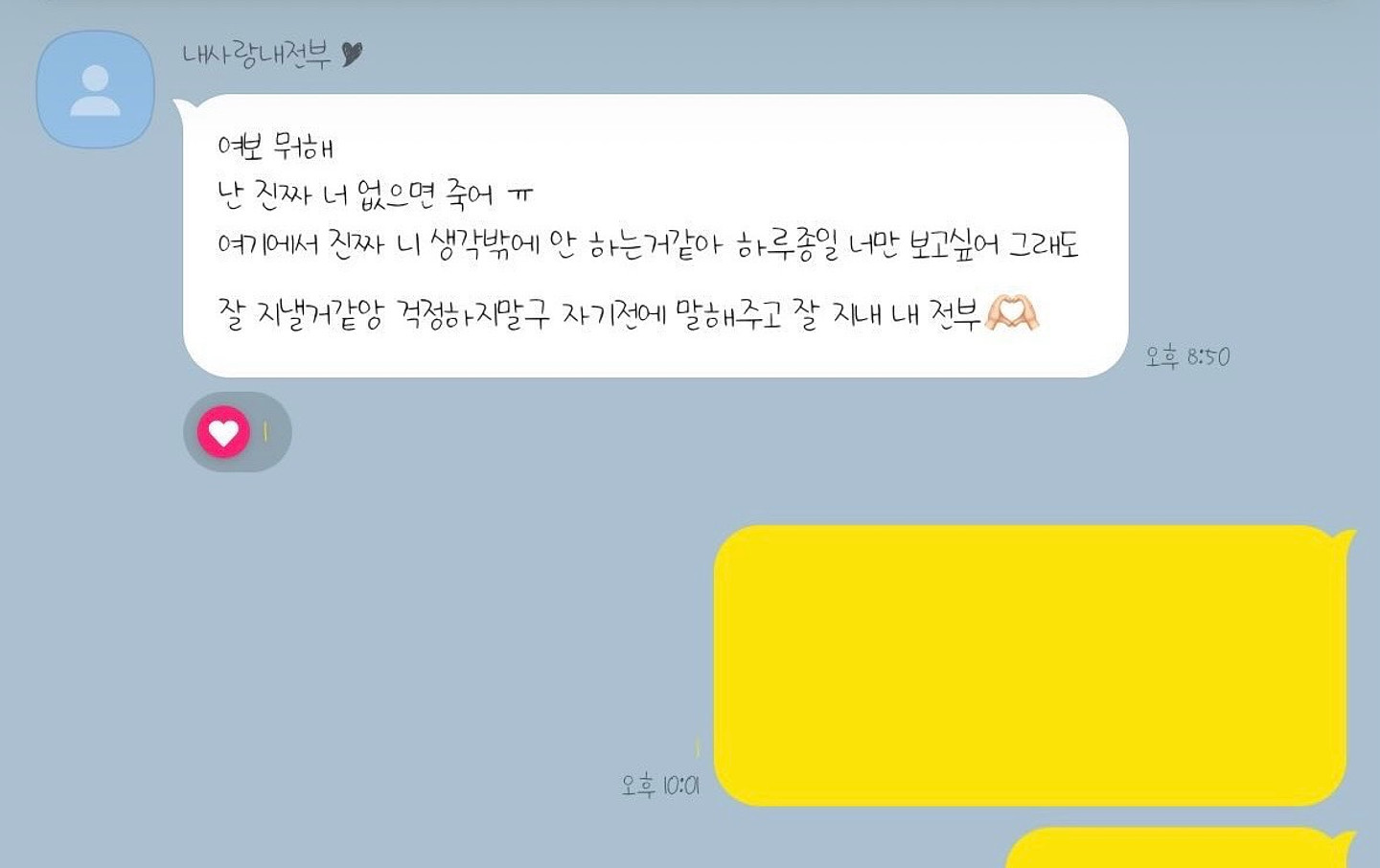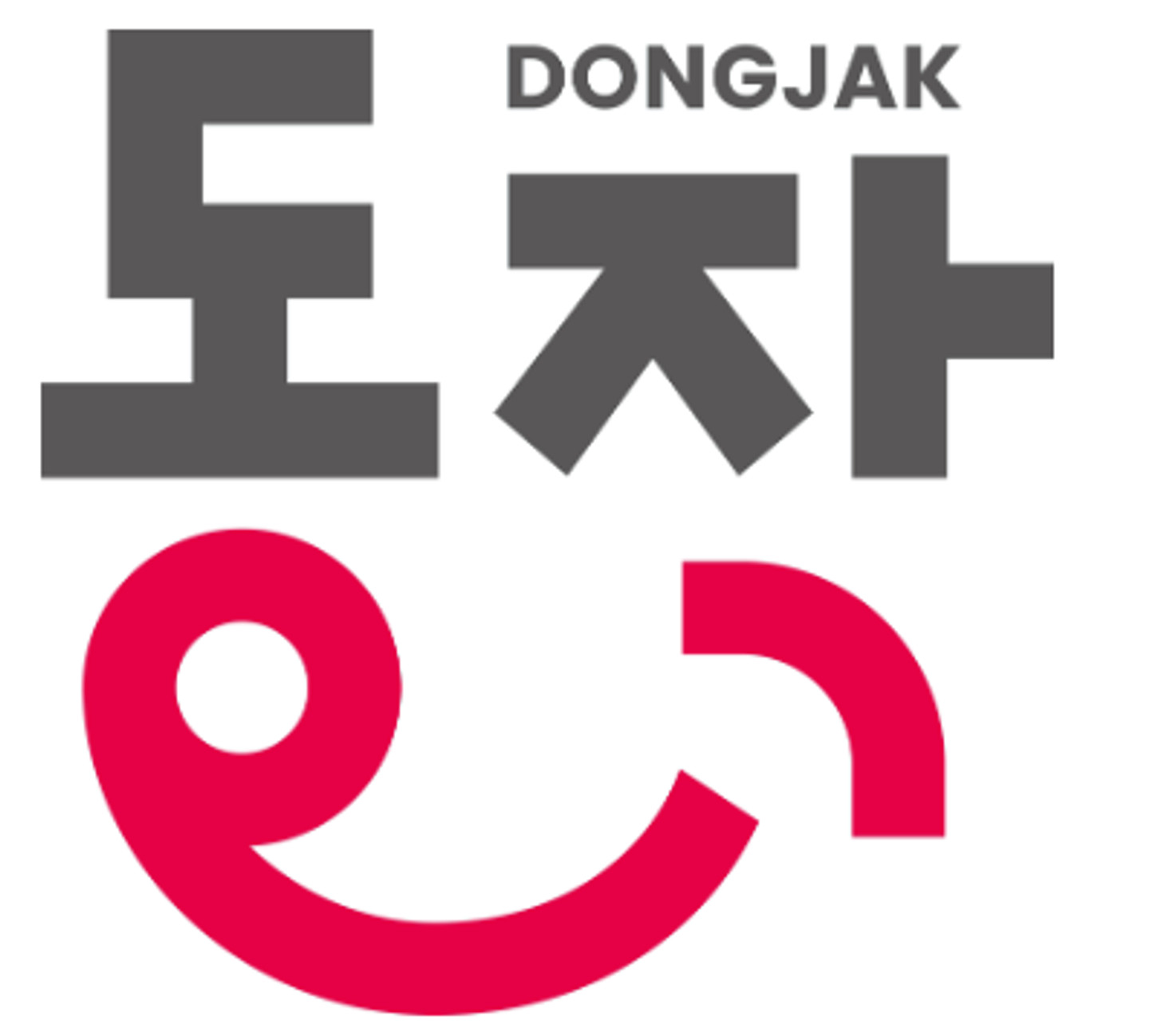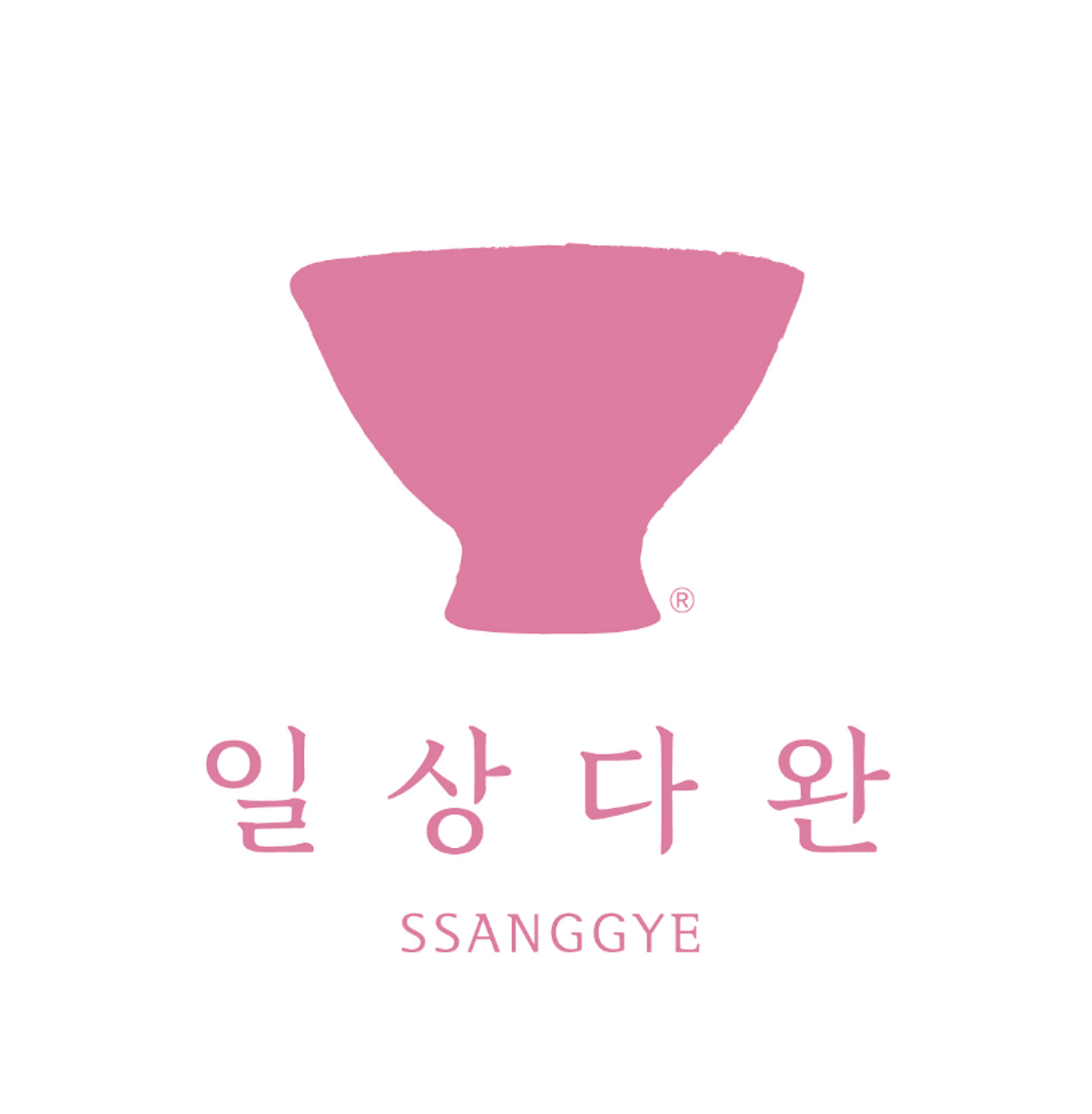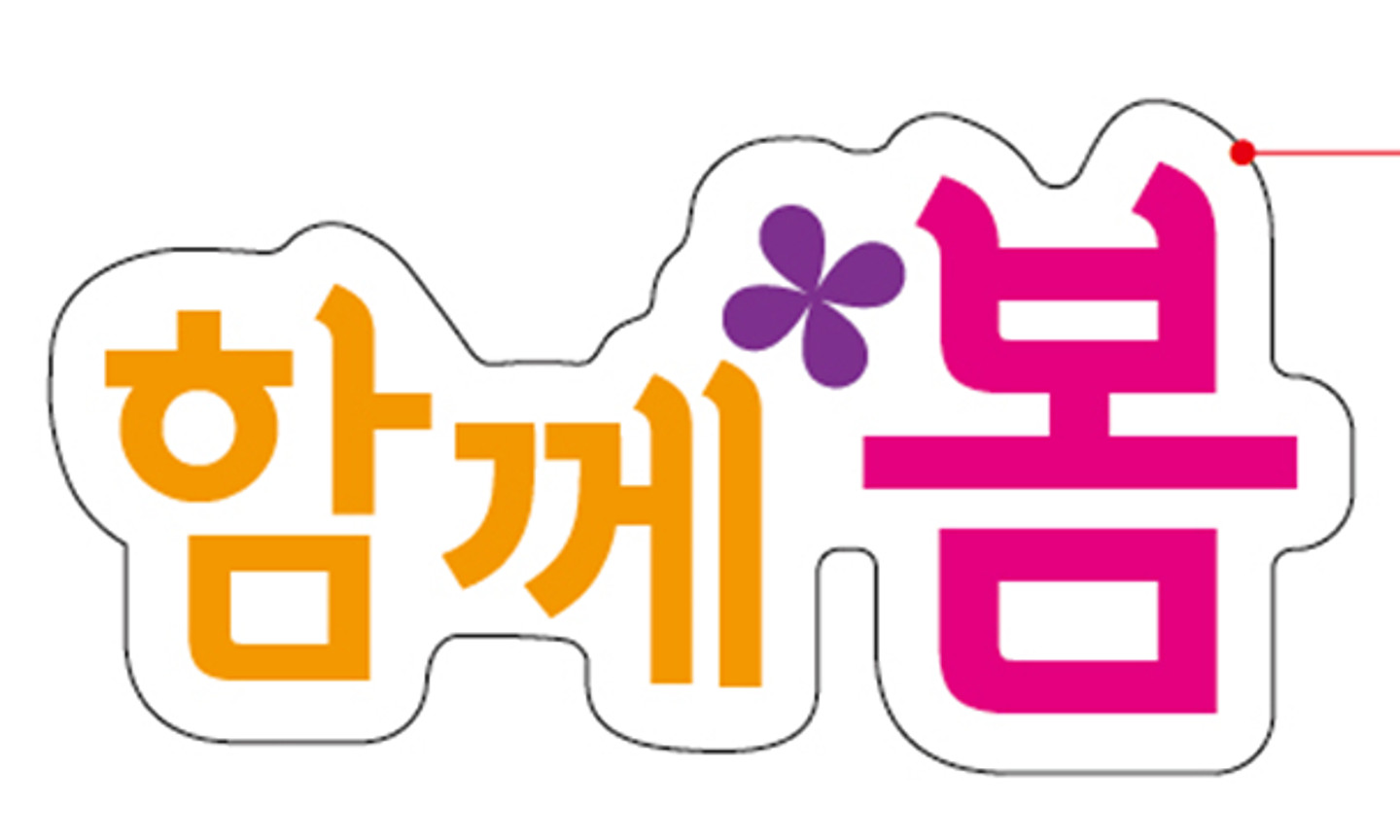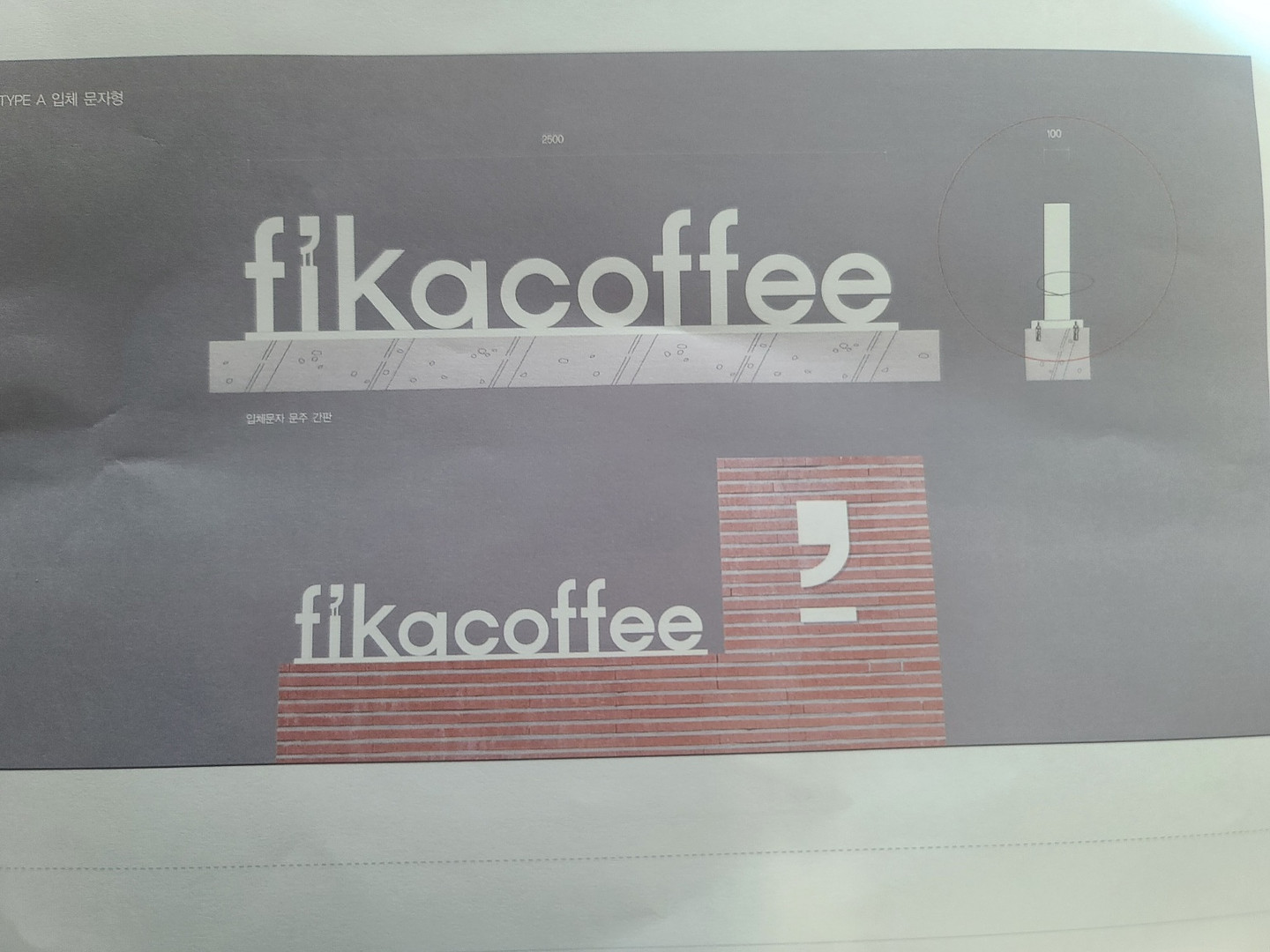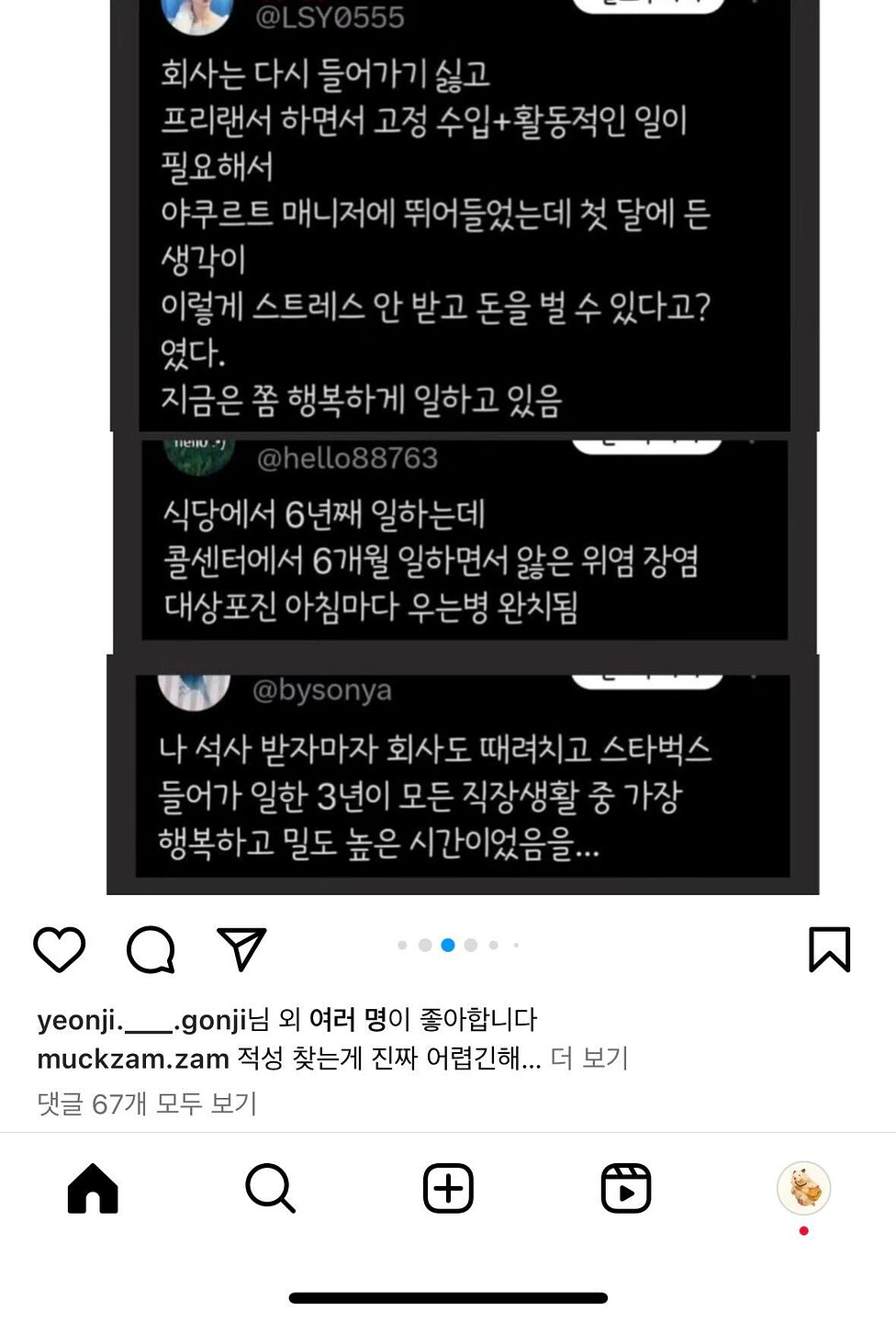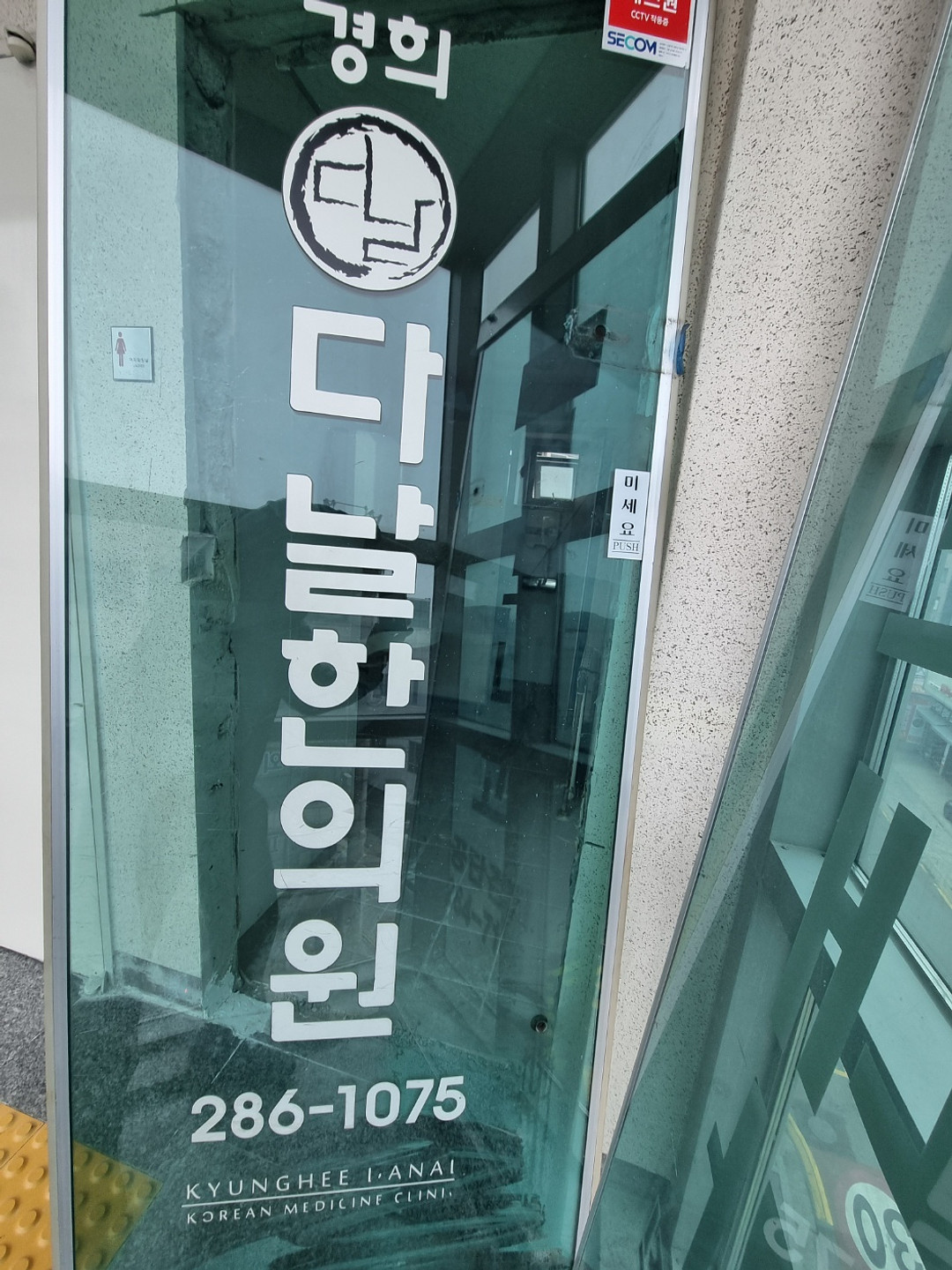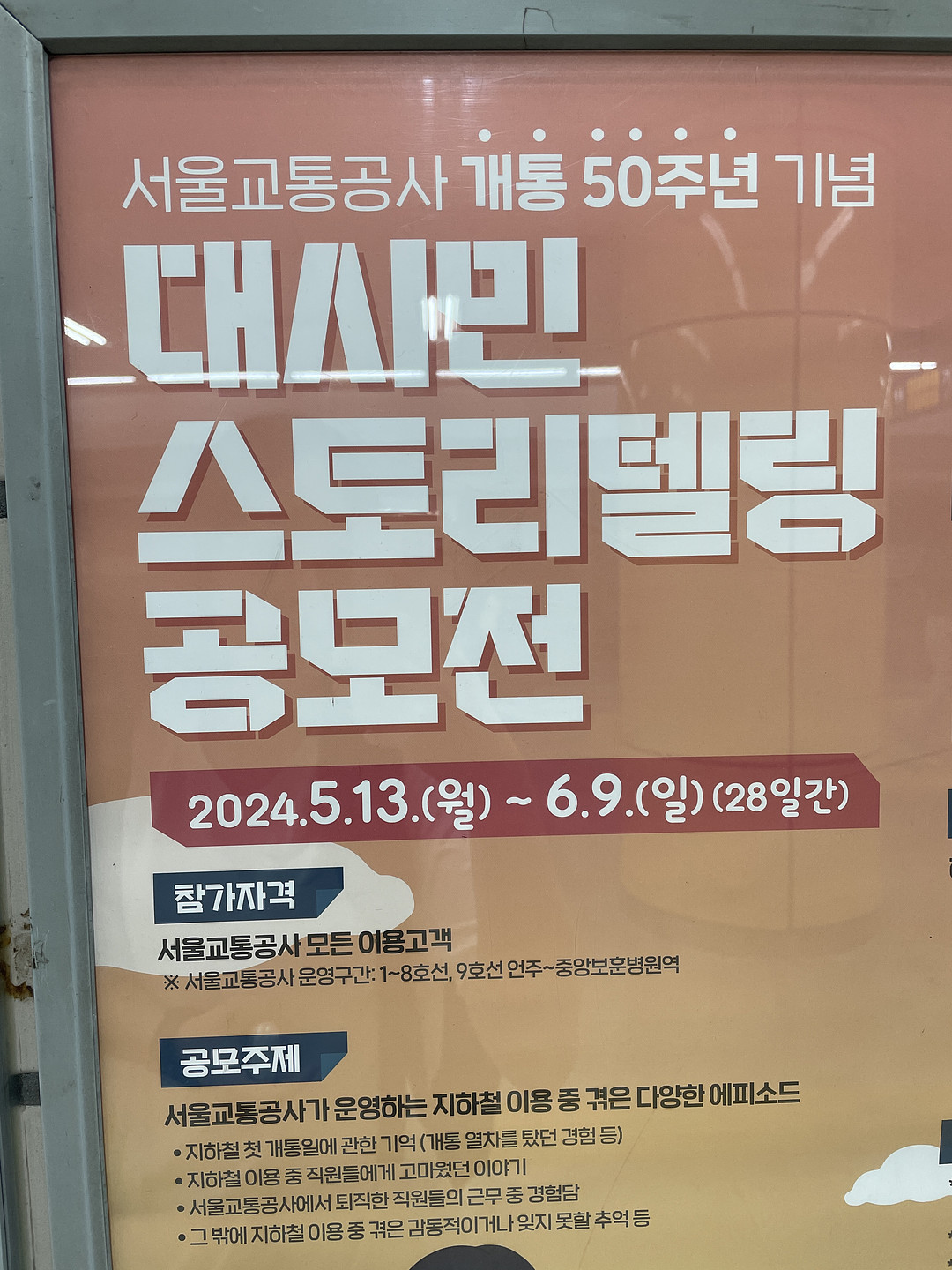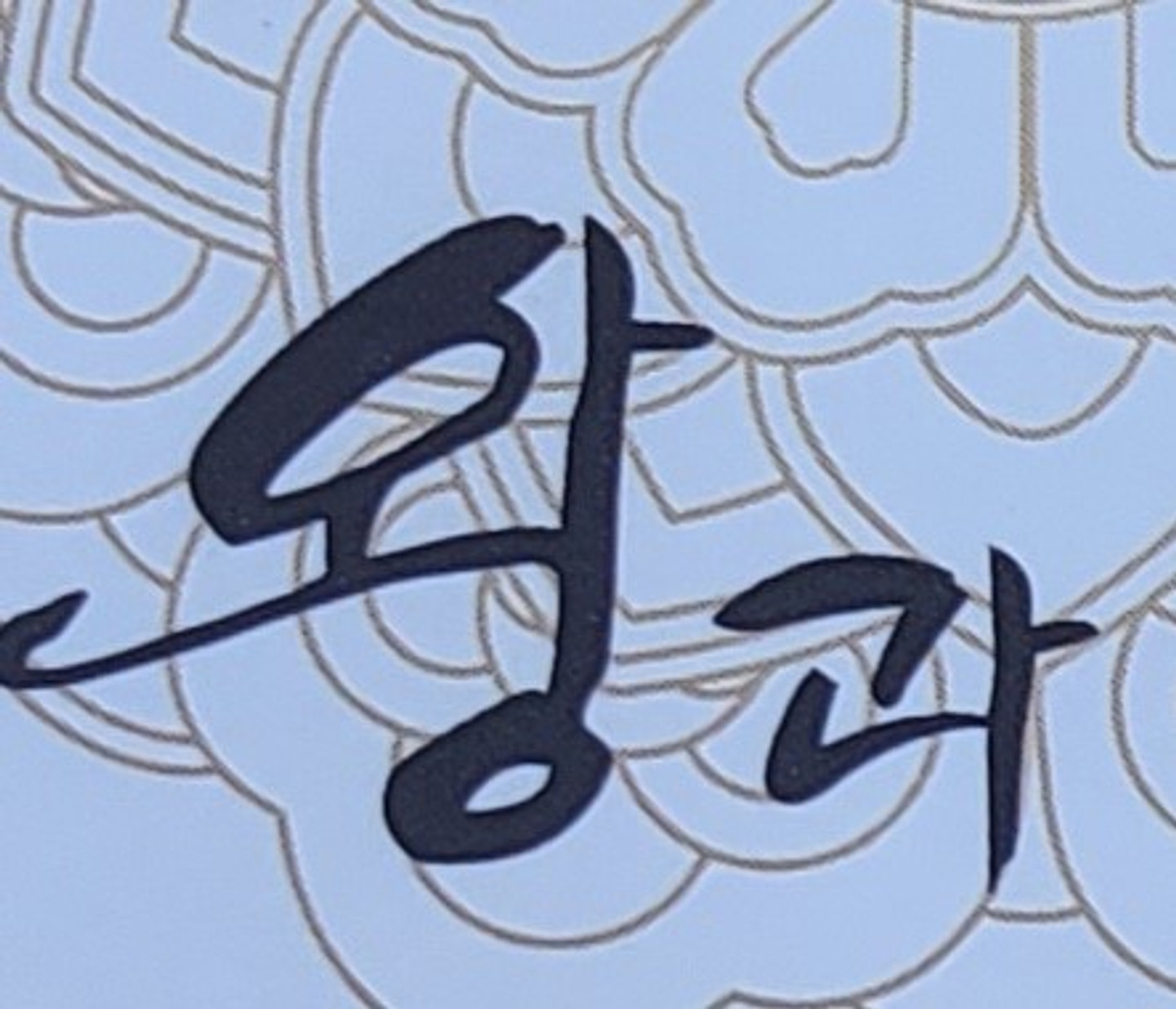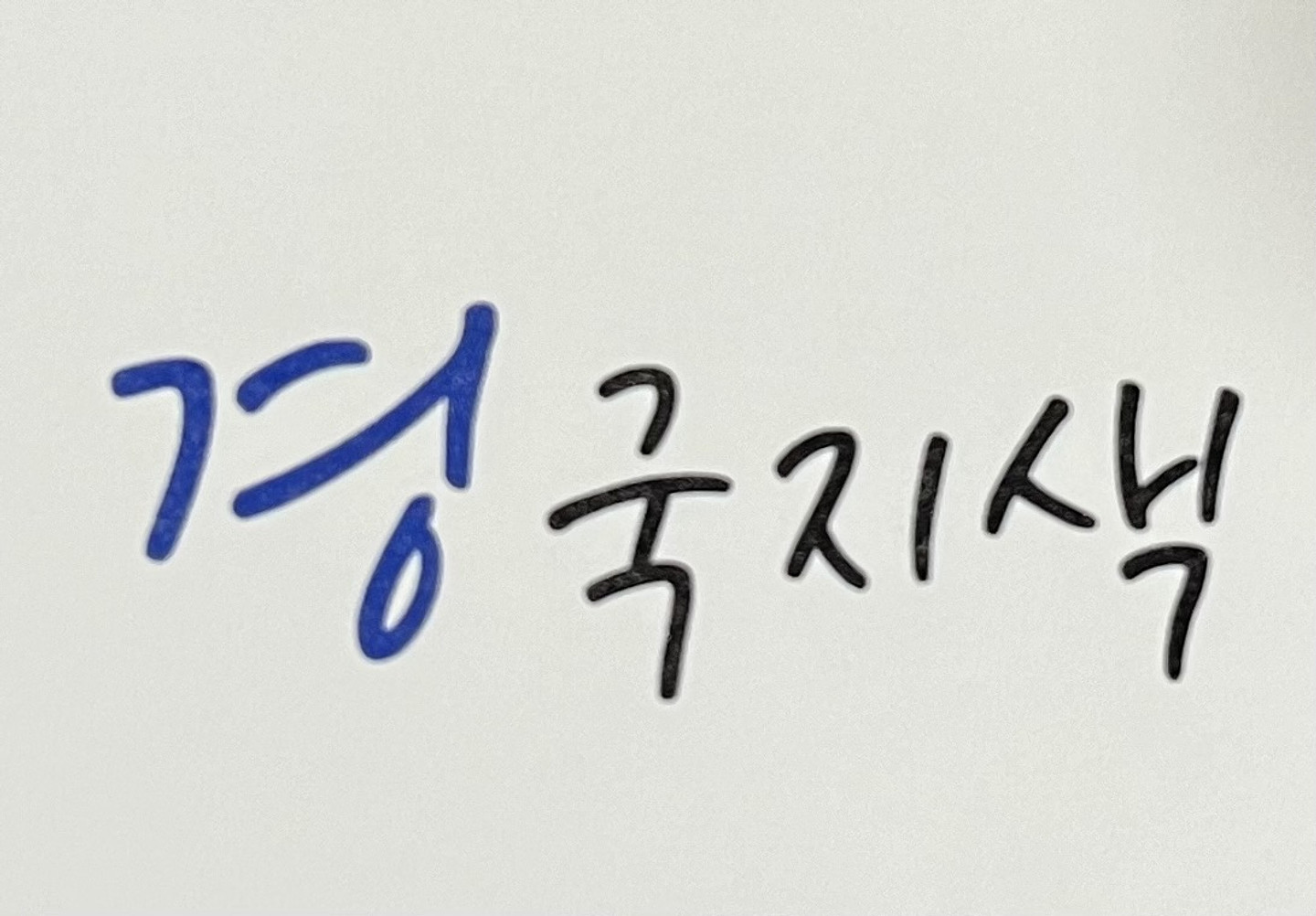
아모레퍼시픽 홈페이지에 있는 폰트인데요! 아모레퍼시픽의 폰트 아리따는 아닌데 홈페이지에 요런 폰트도 있어서 궁금해서 문의드립니다!
궁금해요 ㅠ
ㅇ부분이 태나다체인줄 알았는데 태나다체와는 다르더라구요 혹시 어떤 폰트인지 아실까요 ?
타이틀과 본문에 각각 어떤 폰트가 사용된 걸까요?
검색햇는데 ㅁ 비슷한건 많은데 딱떨어지는 폰트를 못찾았습니다..
요거 영문 폰트 뭔지 아시는 분?
KARMA BLACK CUBE 폰트가 궁금해요… 비슷한거라도 알려주세요 감사합니다
이 폰트 아시는 분 계실까용??
이거 배경있는 폰트로 쓸건데 폰트가 뭔가요?
제목폰트랑 문학과지성사 폰트 뭘까요~?
이 글씨 알려주시면 감사하겠습니다!!
폰트 알고 싶어요
여기 사용된 폰트 궁금합니다.
유혜주 유튜브 폰트입니다!
저 DAY3 폰트 뭘까요
우연히 발견했는데 어떤 폰트인지 궁금해요!
유혜주 브이로그에 나온 폰트입니다
폰트 알려주새용 ㅜㅜ
익스큐즈미...폰트.....알려주세y0... 감삼다 ㅠㅠ
폰트명
비누비누 브랜드에서 쓰는 이 한글폰트좀 알려주세요ㅜㅜ
이거 영문 폰트 뭐죠? 예전에 찾았던 것 같은데 못 찾겠네요 ㅠㅠ
안성재가 여는 미식의 공간 | LG 디오스 오브제컬렉션 김치톡톡 광고에서 쓰이는 이 폰트는 어떤 폰트인가요? 유료라면 비슷한 무료폰트 알려주세요.
무슨 폰트인지 너무 궁금합니다아아앍....,.....,,,,,,,!!!!!!!
이 타이틀 폰트 이름 무엇인가요??!
경기천년바탕체랑 굉장히 유사한데 볼드한 느낌이 강한 폰트입니다.
폰트 이름 좀 알려주세요.ᐟ.ᐟ.ᐟ
폰트 이름 좀 알려주세요! 업로드한 사진이 흐릿해서 잘 안보일겁니다 죄송합니다...
"주니어오디션" 이 폰트 뭔가요?
카톡폰트로 적용하고 싶은데 이름 좀 알려주세요 부탁드립니다 ㅠㅠ...
요즘 자주 보이던데 ㅜㅜ 산돌에는 안 나오고.. 어떤 폰트일까요?
글씨체만 궁금합니다ㅏ!!
이 폰트 너무 궁금합니다!!! 비슷한 폰트 추천도 해주시면 감사할것같습니다!!
무슨폰트일까요?ㅠㅠ
이게 무슨 폰트인지 아시는 분 있으실까유...?
이폰트랑 비슷한 폰트 있을까요??
"스초생은 겨울이 제철" 무슨 폰트인가요? 레터링인가요?
이 약간 반듯하면서 끝은 동그란 이 폰트 뭘까용..
큰 영문 타이포 폰트가 궁금합니다 :)
무슨폰트인가요
두개 겹쳐서 그림자 효과 준거같은데 폰트 어떤게 사용된걸까요 !
고수님들~이 궁서체는 폰트 이름이 뭘까요? 부탁드립니다~^^
이 폰트 이름이 뭘까요? 고수님들 부탁드려요
유퀴즈 독립유공자 후손분들 나오신 편에 나오는 붓글씨 같은 저 폰트 알 수 있을까요?
무슨 폰트일까요? 손글씨일까요??
이 서체가 뭘까요? 예전에 한참 많이 썻던 서체 같은데 도무지 기억이 안나요 도와주세요
폰트 이름 궁금합니다. 미리 감사드립니다~
어떤 폰트일까요? 고운바탕등 여러가지를 봤는데 ㅅ자랑 몇가지 부분이 아닌것 같아서요.
이 폰트는 뭘까요 ? ㅡㅜㅡ
해당 이미지에 활용된 폰트 이름을 알고싶습니다. 그리고 혹 해당 이미지와 비슷한 무료 폰트가 있다면 해당 폰트 정보도 알려주셨으면 합니다. 답변을 주신 모든 분들께 감사드립니다.
간절하게 폰트 알고 싶어요.. ㅠㅠ
해뜨는 서산화 문화시설사업소라는 이름명의 폰트가 뭔지 궁금합니다 만든거같기도 하고 ㅠ 급한데.. ㅠㅠ 검색해도 안나오네요
영어 kids day 폰트명 궁금합니다!
이 폰트 이름이 뭔지 궁금합니다
정말 알고 싶은데.. 이거 혹시 무슨 폰트일까요?